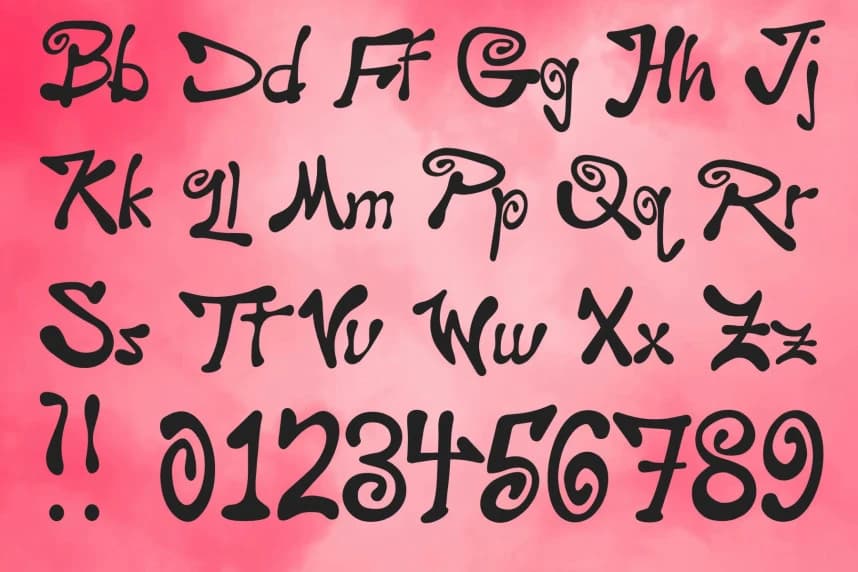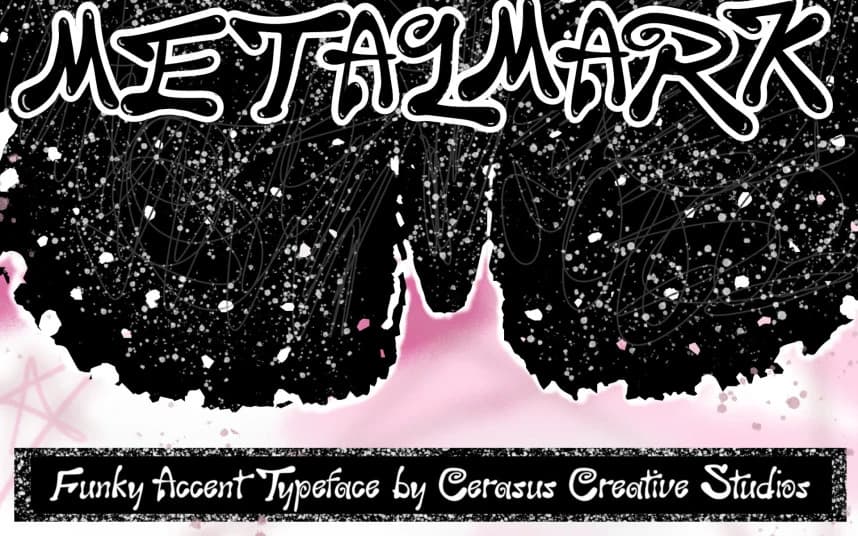
Starry Metalmark Font
Starry Metalmark Font, retro esinli tipografiyi burkulmuş, dekoratif harf biçimleriyle birleştiren funky ve psikedelik bir gösterim yazı tipidir. Dönen kıvrımlar, bozulmuş şekiller ve sanatsal ayrıntılar içeren bu yazı tipi, göz alıcı yaratıcı profesyoneller için mükemmel olan cesur ve ifade dolu bi
Starry Metalmark Font, garip ve psikedelik bir gösteri yazı tipidir; retro esinli tipografi ile eğrilmiş, dekoratif harf biçimlerini bir araya getirir. Dönen kıvrımlar, bozulmuş şekiller ve sanatsal ayrıntılarla bu yazı tipi, göz alıcı yaratıcı projeler için mükemmel olan cesur ve ifade dolu bir görsel stil yaratır.